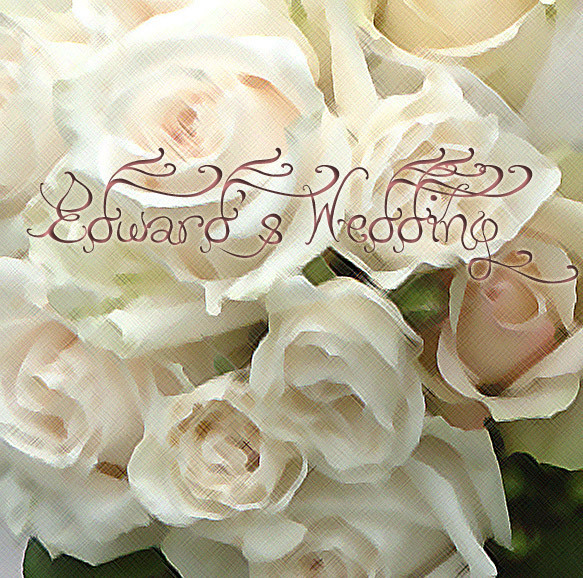
Edward's Wedding
Edward's Wedding è un font script gratuito, interamente ispirato alla calligrafia nuziale formale. Le lettere scorrono in un ritmo leggero e sinuoso, caratterizzato da lunghi tratti ricurvi e fioriture aeree che donano al font un aspetto cerimoniale, tutt'altro che informale.
Si adatta perfettamente a inviti, "save the date", segnaposto, etichette per champagne e packaging ricercati, dove un look romantico e autografo è fondamentale. Essendo un font gratuito, è ideale anche per copertine, titoli e piccoli elementi di branding che traggono vantaggio da quegli ampi tratti di ingresso e uscita, soprattutto quando si desidera che le parole trasmettano la sensazione di essere state scritte appositamente per l'evento.